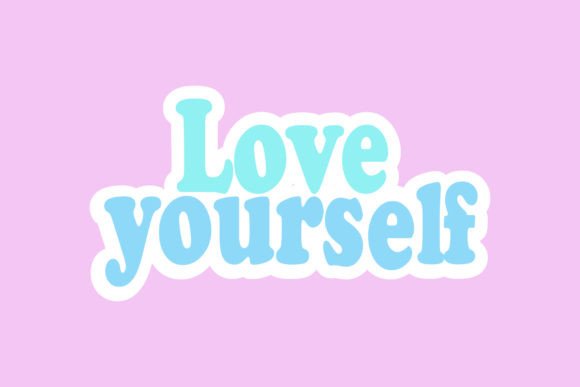
Cute Typography Love Yourself
Trabalhado com precisão, Cute Typography Love Yourself fornece vetores limpos, tipografia suave e uma licença comercial para sua tranquilidade.